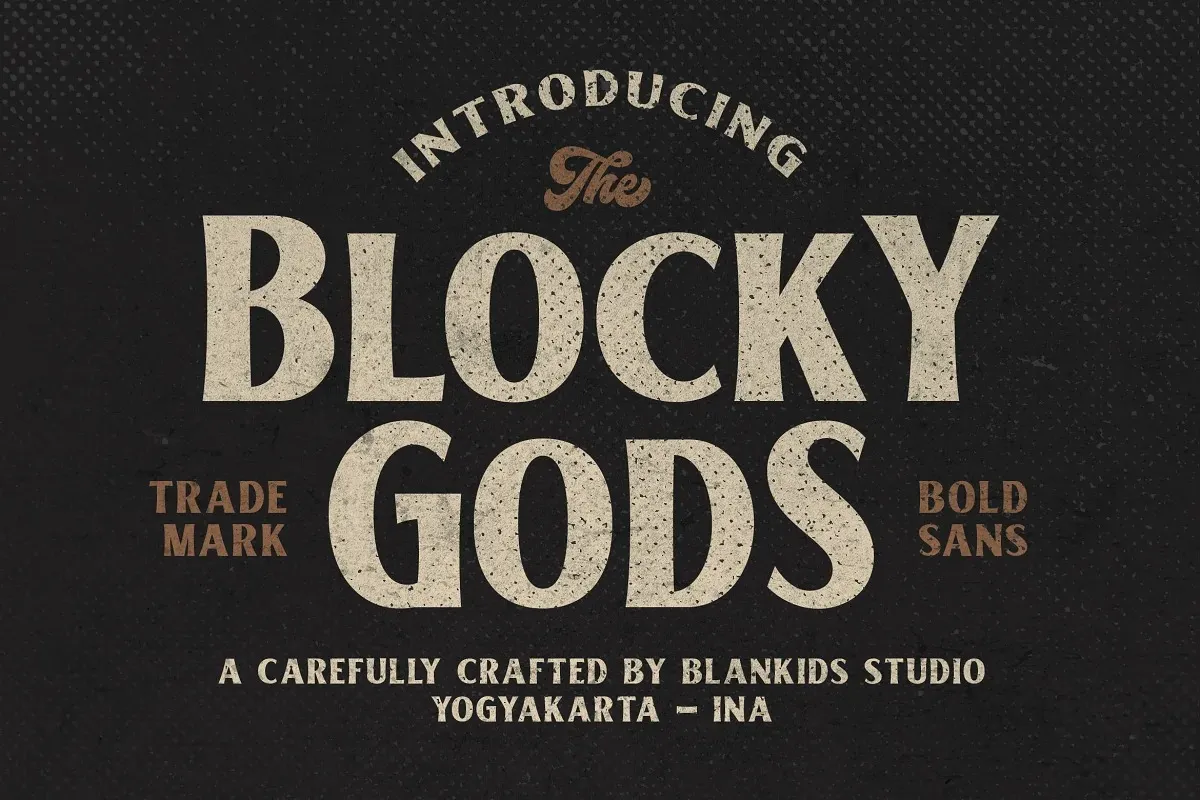
Blocky Gods Font – Download Grátis
Esta fonte de exibição ‘Blocky Gods’ é uma explosão de estilo vintage inspirada nos antigos selos do Oeste Estéril e na arte de motocicletas. Inspirada no design retro, ela traz à tona um tema divertido e perfeito para uso em elementos de exibição, como roupas personalizadas, signos de citação ou logotipos. Seja você designer de moda, criador de artesanato ou simplesmente um entusiasta de design gráfico em busca de algo único, ‘Blocky Gods’ certamente se encaixa perfeitamente em suas necessidades. Com seu estilo robusto e característicos geométricos marcantes, esta fonte é uma escolha inteligente para qualquer projeto que exija destaque e criatividade.